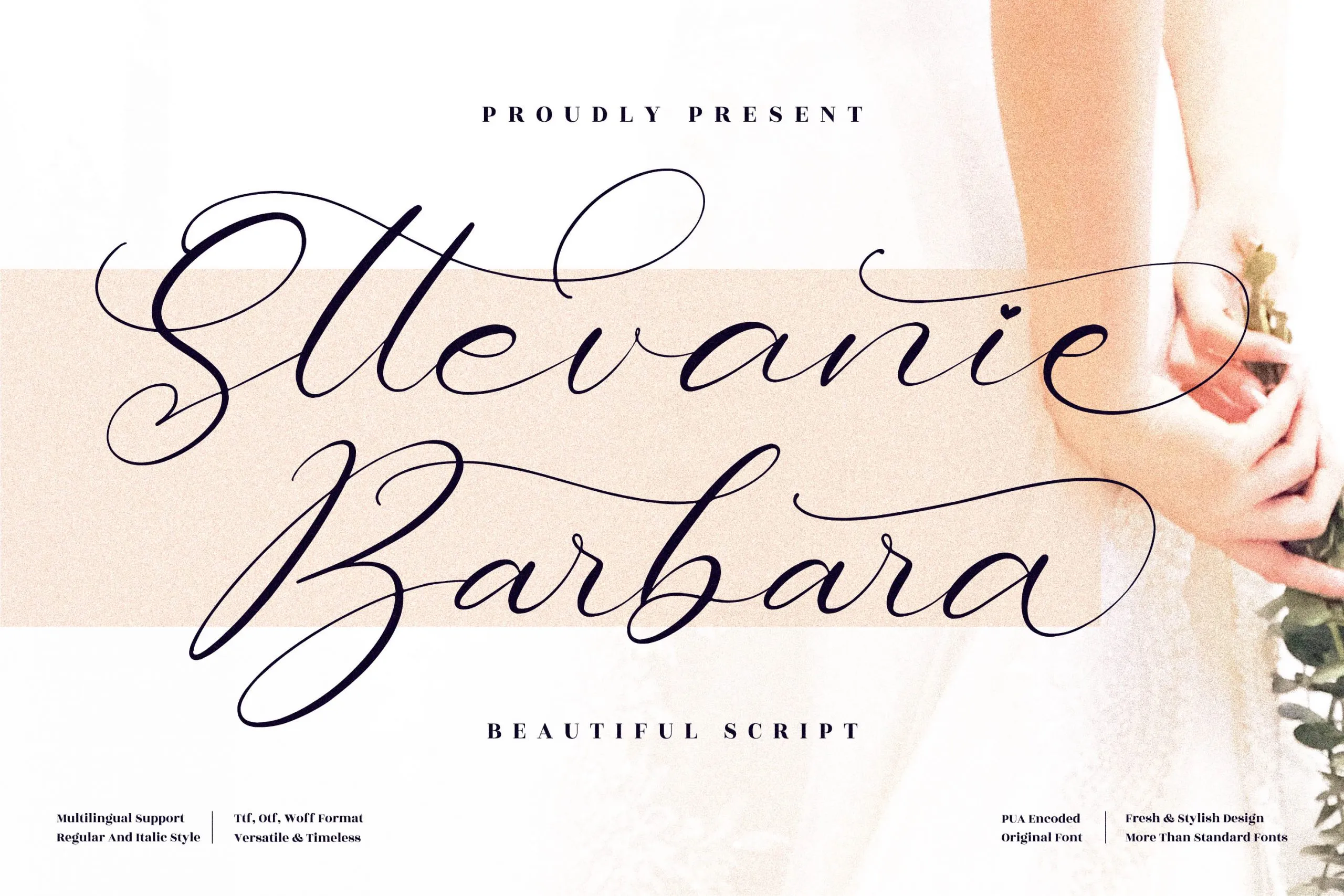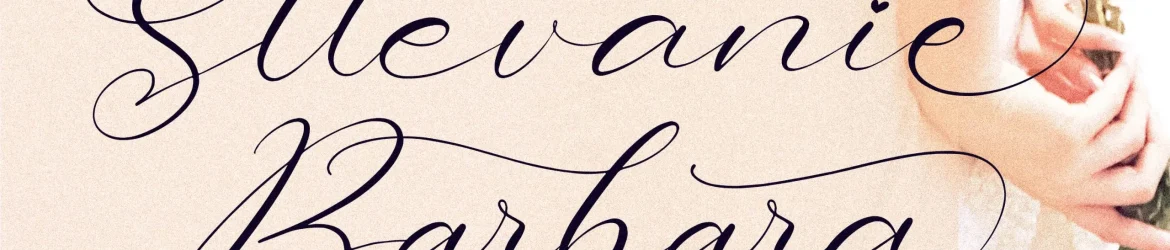
Sttevanie Barbara Font – Download Grátis
Esta é uma fonte de calligrafia romântica ideal para projetos diversos que exigem um toque elegante e autêntico. Com seu design delicado, a Sttevanie Barbara será perfeita para criações como logotipos, embalagens de produtos, pacotes de alimentos, etiquetas, cartões personalizados, presentes de agradecimento e até mesmo fotografias e assinaturas. Suas linhas suaves e detalhes elegantes se adaptam perfeitamente para qualquer aplicação visual que você possa imaginar, tornando-a uma escolha ótima tanto para designers profissionais quanto para criadores mais desafiados em busca de um toque de sofisticação e autenticidade. Adquira a Sttevanie Barbara Font hoje e dê vida à sua próxima obra prima!